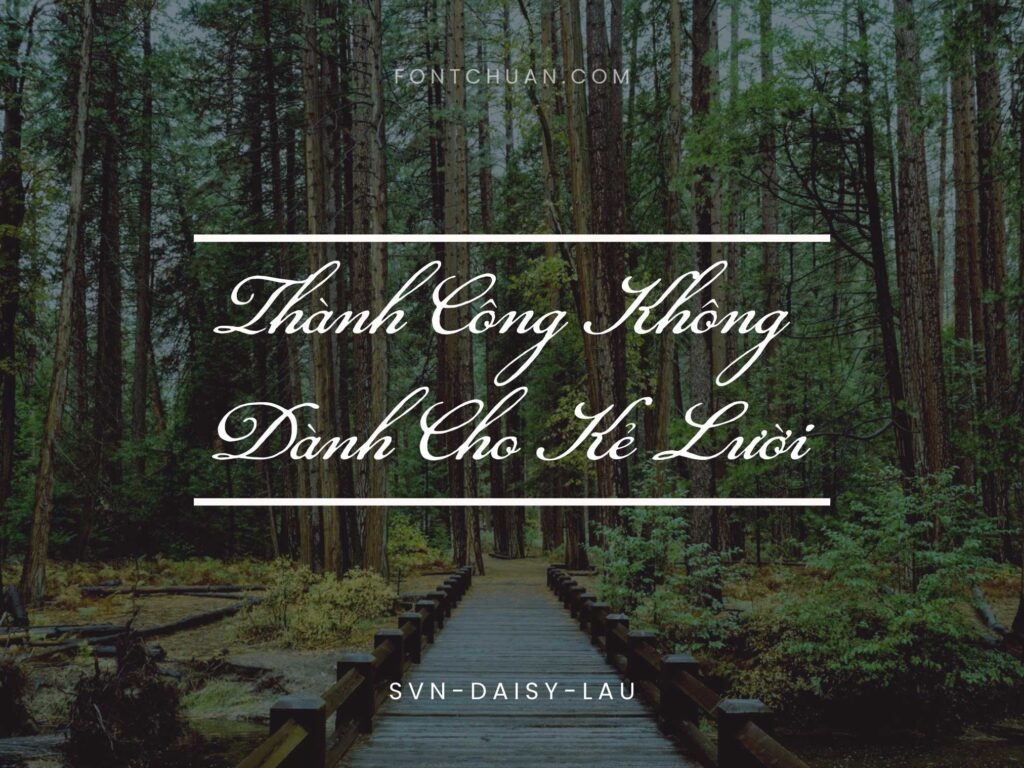
Font SVN Daisy Lau Việt Hóa
Tác giả Font: Ryoichi Tsunekawa
Daisy Lau là một font chữ script dựa trên kiểu chữ viết tay của các quý cô Hong Kong vào thế kỷ 19, được thiết kế bởi Ryoichi Tsunekawa. Font này mang lại cảm giác viết tay chân thực nhờ vào kết cấu mực in độc đáo. Daisy Lau đã được Việt hóa để hỗ trợ tiếng Việt bởi Styleno.1 Fonts, đồng thời hỗ trợ nhiều ngôn ngữ khác, giúp mở rộng phạm vi sử dụng trên toàn cầu. Font này được thành viên của Font Chuẩn sưu tầm và chia sẻ, đáp ứng nhu cầu của bạn đọc và ứng dụng thực tế vào các dự án thiết kế.
Đặc điểm thiết kế của Daisy Lau bao gồm các nét chữ viết tay tinh tế, tạo cảm giác thanh lịch và cổ điển. Font này phù hợp cho các ứng dụng như thiết kế thiệp cưới, tiêu đề, logo, bài đăng trên mạng xã hội, quảng cáo và bao bì sản phẩm. Các ngành nghề phù hợp bao gồm quảng cáo, nghệ thuật và thiết kế đồ họa.